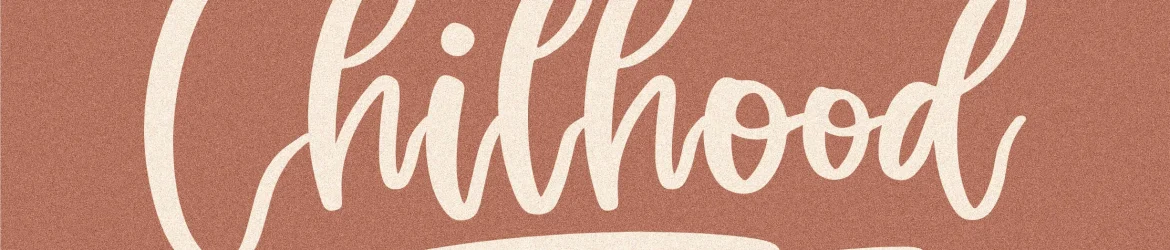
A fonte “Chilhood” é uma elegante seleção entre os diversos tipos de fontes manuscritas disponíveis para projetos digitais ou impressos. Sujeitada a um vasto leque de usos, como logos e marcas de projeto, design para móveis de casa, embalagens de produtos, xícaras personalizadas, frases em cartazes, sacolas de compras, camisetas, capas de livros, cartões de nome, cartões de convite, cartões festivos, etiquetas e até mesmo fotografias e logotipos, a fonte “Chilhood” é ideal para criar uma atmosfera única e delicada. Com sua escrita fluida e natural, a fonte “Chilhood” traz um toque de personalidade e encanto que é perfeito para aquelas criações onde o detalhe faz toda a diferença. Seja em pequenos elementos ou no design de uma imagem completa, esta fonte manuscrita tornará seu trabalho ainda mais especial e sofisticado. A “Chilhood” não é apenas um recurso gráfico, mas sim uma maneira de dar vida aos seus projetos digitais, adicionando uma aparente autenticidade e charme que fazem toda a diferença em qualquer projeto. Sujeitada a vários usos e aplicabilidades, o Chilhood font cativa não apenas os olhos dos espectadores, mas também seu coração com seu toque delicado e encantador.